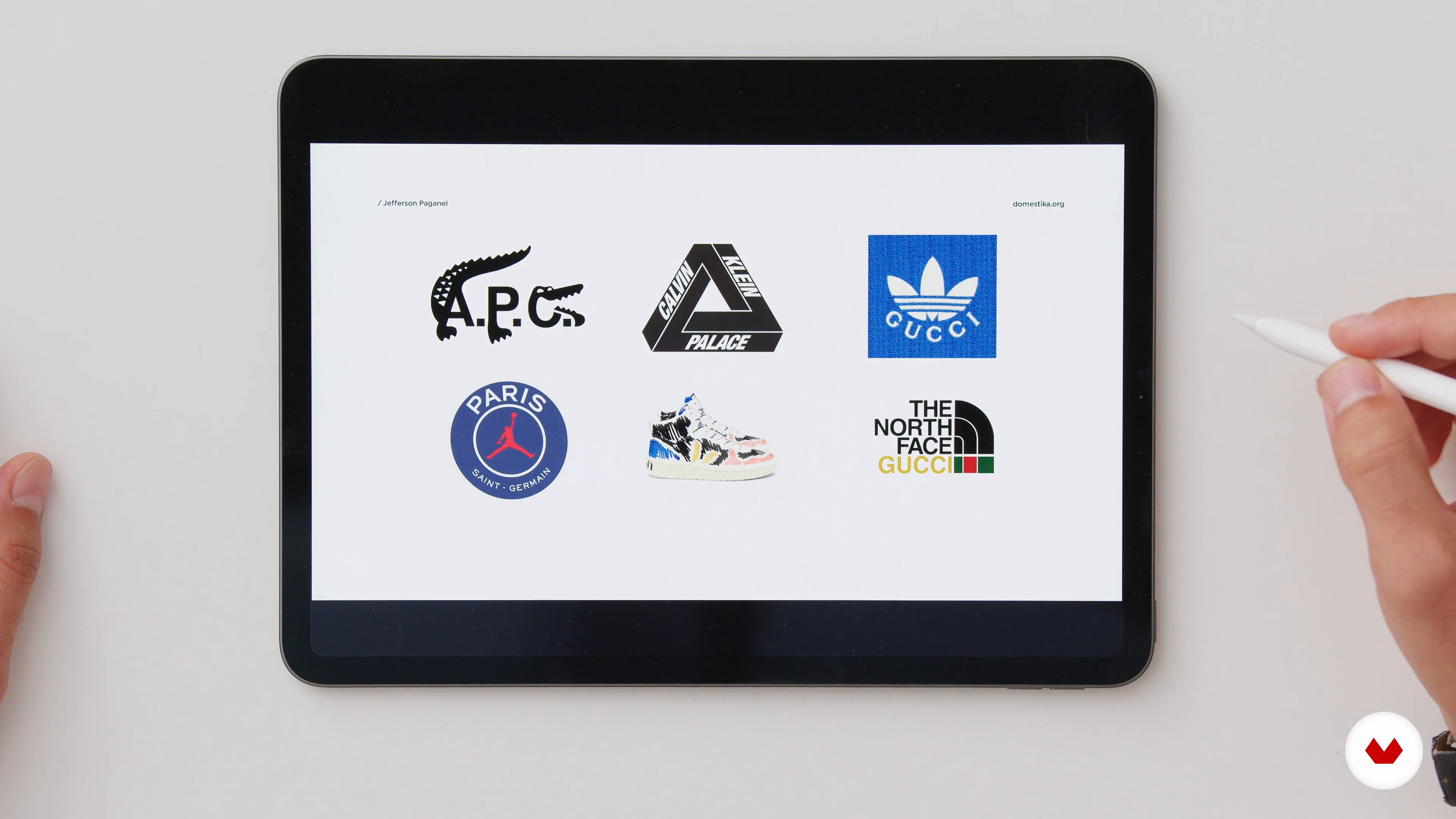
Logodesign: Vom Monogrammdesign bis zum Text
Monogramm vs. Typografie
Über die Videolektion: Monogramm vs. Typografie
“In dieser Lektion erkläre ich die vielfältigen Möglichkeiten von Logos und ihren Symbolen.”
In dieser Videolektion behandelt Jefferson PAGANEL das Thema: Monogramm vs. Typografie, das Teil dieses Domestika-Onlinekurses ist: Logodesign: Vom Monogrammdesign bis zum Text. Gestalte in diesem Kurs ein charakteristisches Logo und Monogramm. Designe eine einzigartige Markenidentität..
“In dieser Lektion analysieren wir die Beziehung zwischen Monogramm und Typografie. Finden Sie die richtige Typografie, Es ist die wichtigste Entscheidung für den Aufbau einer Markenidentität. Typografie ist eigentlich die schriftliche Übersetzung dessen, was wir sagen. Typografie symbolisiert eine Ära, ein Anker, Werte. Um die perfekte Typografie zu finden, sind einige Kenntnisse und auch viel Recherche erforderlich Abhängig von der typografischen Wahl, die Sie treffen, es wird notwendigerweise Dinge in Bezug auf die Marke hervorrufen. Es ist eine echte Komplexität, die richtige Typografie ...”